逐浪雅宋体是一款充满艺术气息的简体中文汉字,逐浪字体最大的特色就是加入了现代美术的元素,让整个字体看起来非常的大气,一般试用于广告设计,平面设计,报纸杂志,喜欢的朋友们可前往字体视界平台下载。
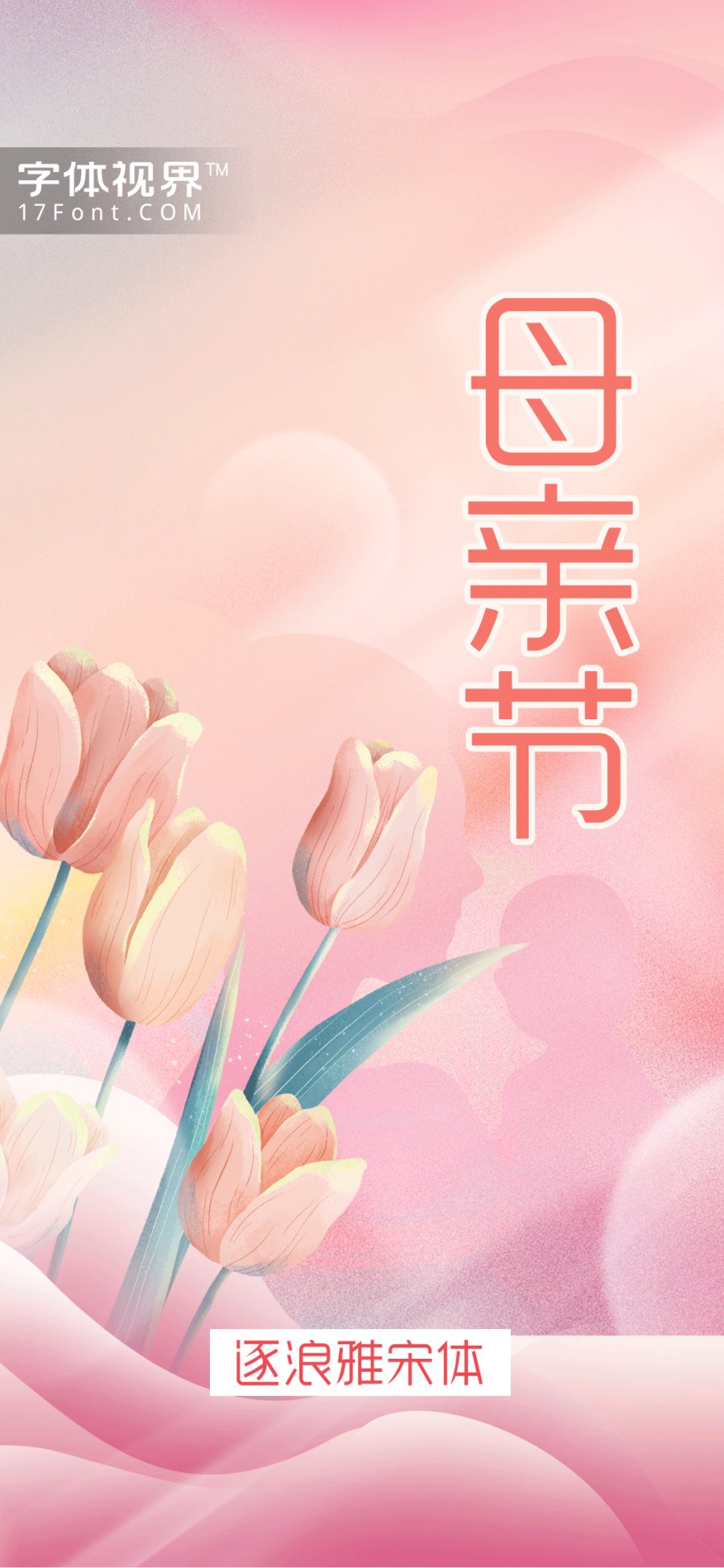
上首云润体,字体整体修长,笔画横细竖粗,每个笔画都圆形倒角,除横竖笔外,其他笔画都是两端粗细不一,使得字体简洁但又不失于活泼灵动,适用于搭配标志、广告标语、商业广告、海报字体等高端属性。
三极小城飘逸体字形洒脱,连笔随形变化在行书的基础上更灵动多变,笔画灵动呼应手写感十足,适合于文创产品、电影海报、包装、品牌名称海报、媒体标题屏显等。